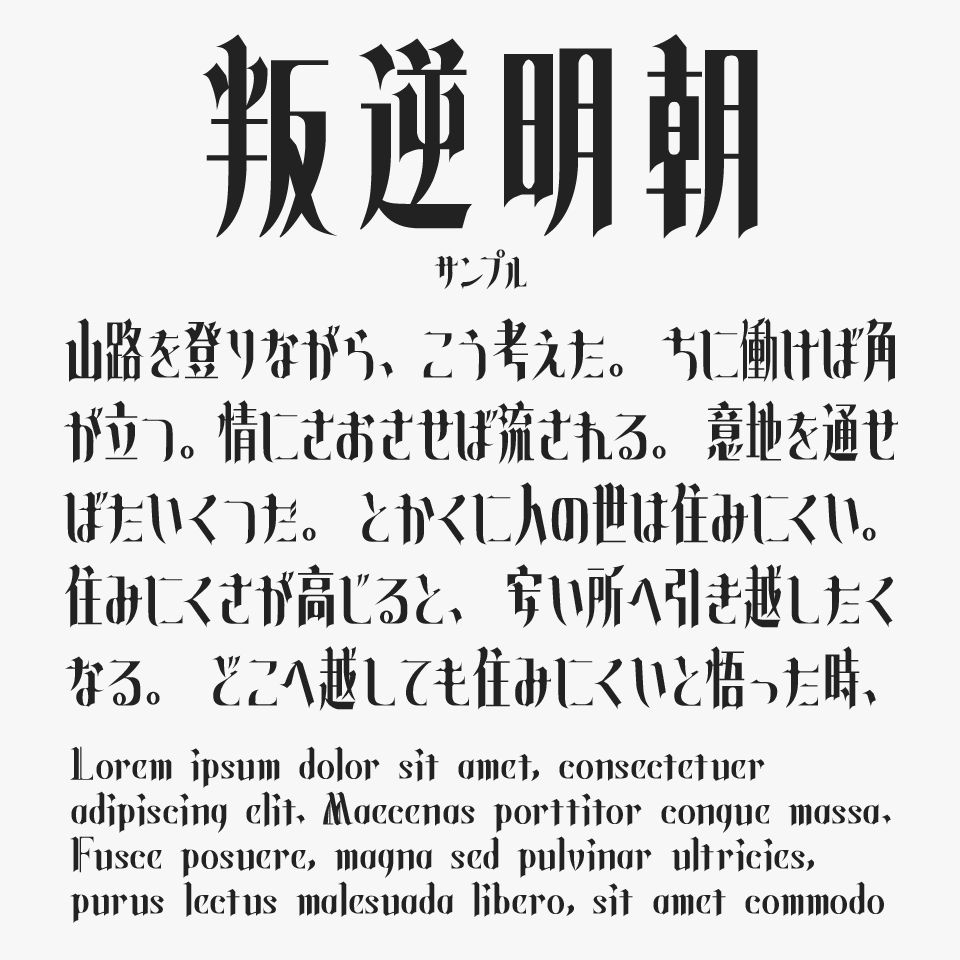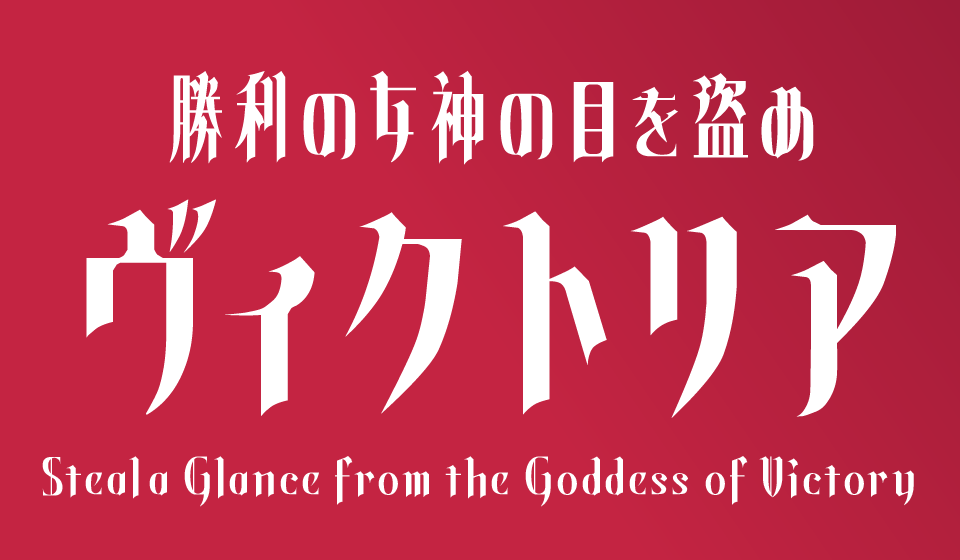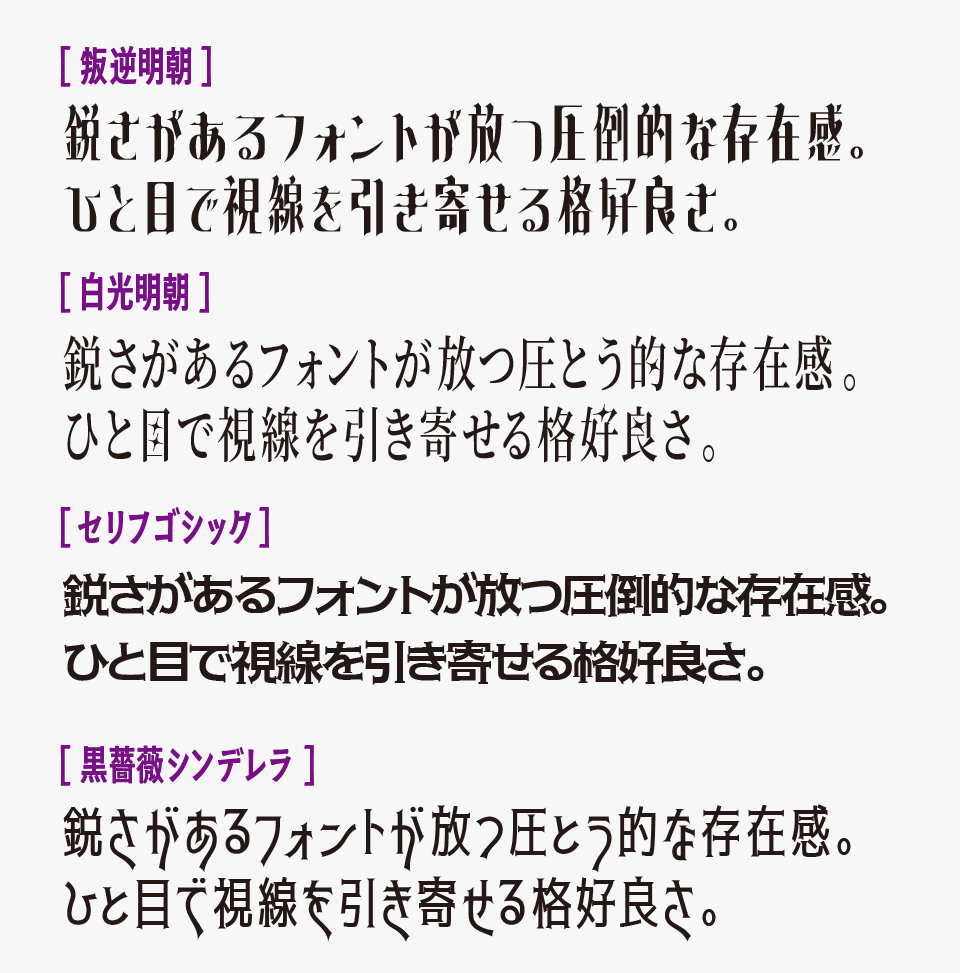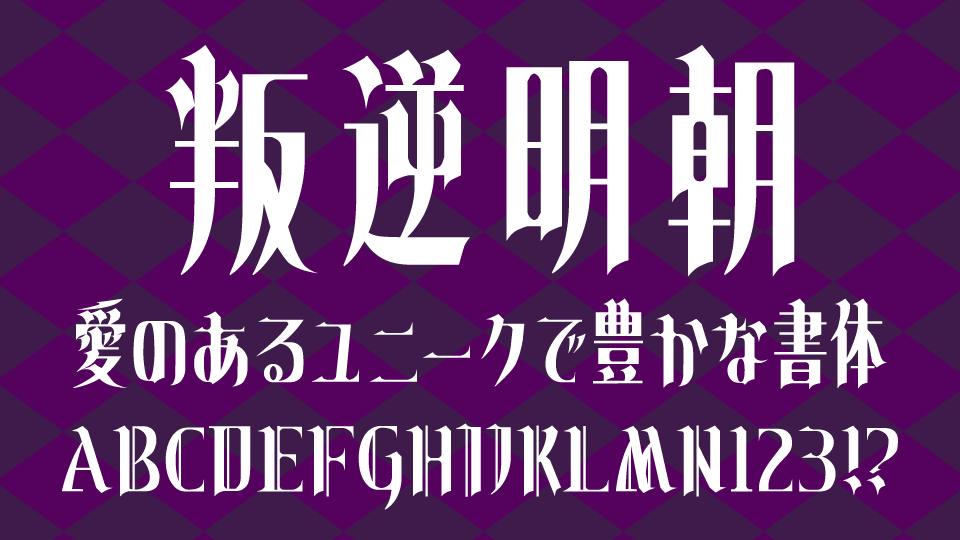
叛逆明朝(Hangyaku)フォントは、『魔法少女まどか☆マギカ 叛逆の物語』のロゴをモチーフに制作された、装飾性の高いデザイン明朝体フォントです。
文字の先端には繊細な装飾が加えられており、ゴシックロリータのような世界観や、エレガントさの中にどこか妖しさや退廃的な雰囲気を感じられるフォントです。
そのままベタ打ちするだけでも、アニメ・ゲーム系のロゴのような印象的なビジュアルを作りやすく、ダークファンタジーやゴスロリ系デザインとも相性抜群です。独特な装飾感と存在感がありながら、文字としての読みやすさも残されている、とても完成度の高いフォントとなっています。
日本語文字のデザインも魅力ですが、ぜひアルファベットにも注目してほしいフォントです。アルファベット部分には、「西洋レトロ」を感じさせるゴシック調の装飾が施されており、どこかブラックレターのような重厚感や妖しさが感じられるフォントとなっています。
叛逆明朝フォントのような装飾性を持つデザインフォントと比較してみると、叛逆明朝フォントは特にシャープで繊細な装飾表現が際立っています。
ゴシック調やブラックレター風の装飾を取り入れたフォントはほかにもありますが、叛逆明朝フォントは、鋭く伸びる先端や縦長のシルエットによって、エレガントさとダークな雰囲気が絶妙に混ざり合っているところは唯一無二の存在です。
比較フォントとして「白光明朝」「セリフゴシック」「黒薔薇シンデレラ」と並べてみると、それぞれ装飾性の方向性が大きく異なっているのが面白いところです。世界観によって印象が大きく変わるので、ぜひあわせて比較しながらチェックしてみてください。